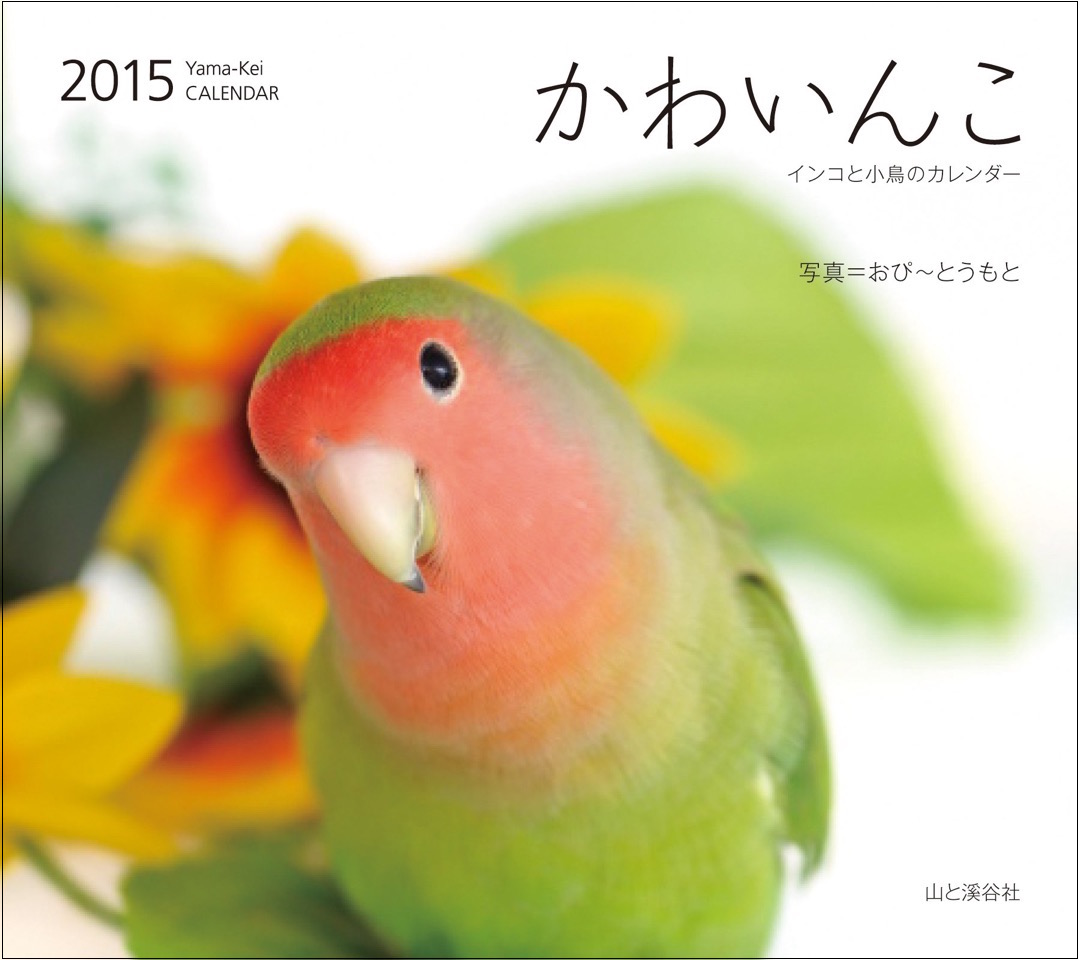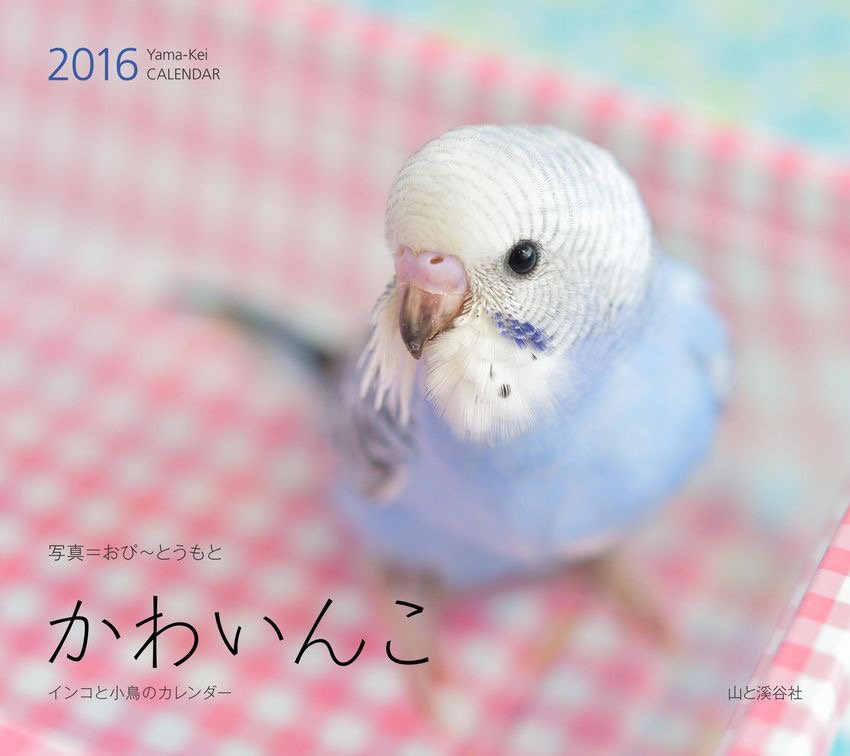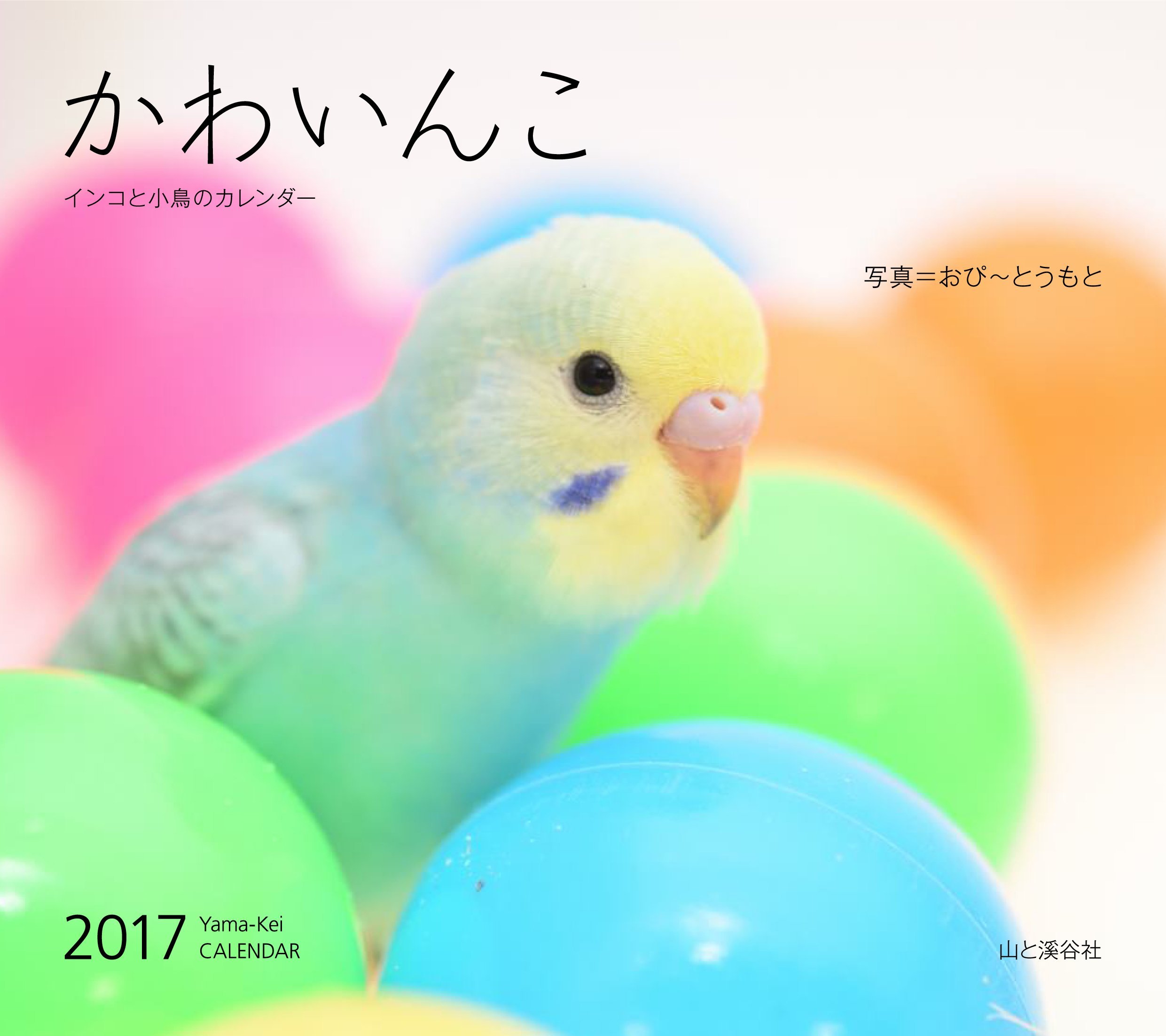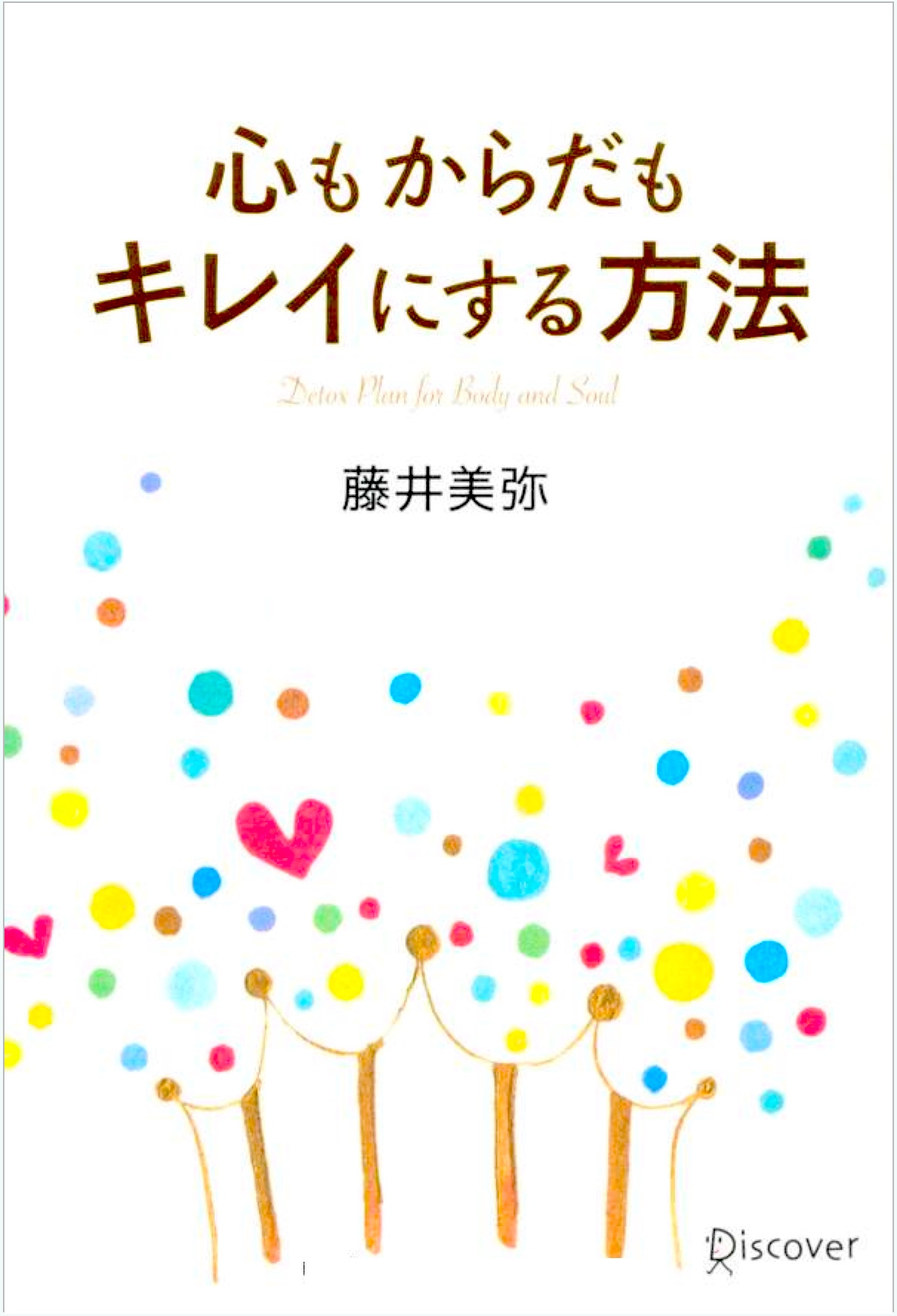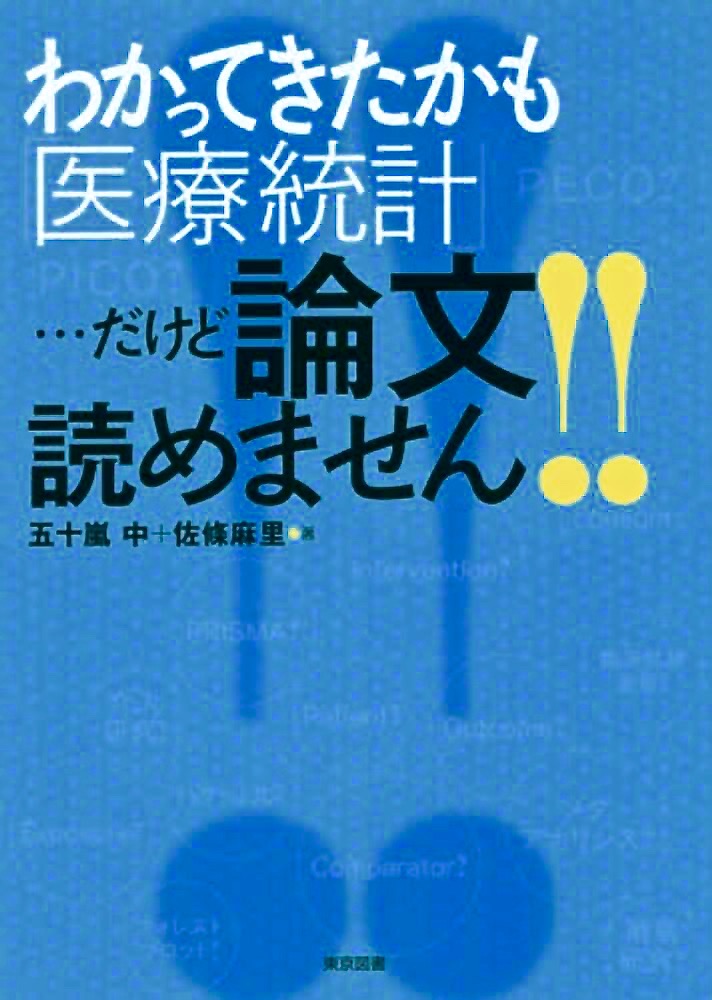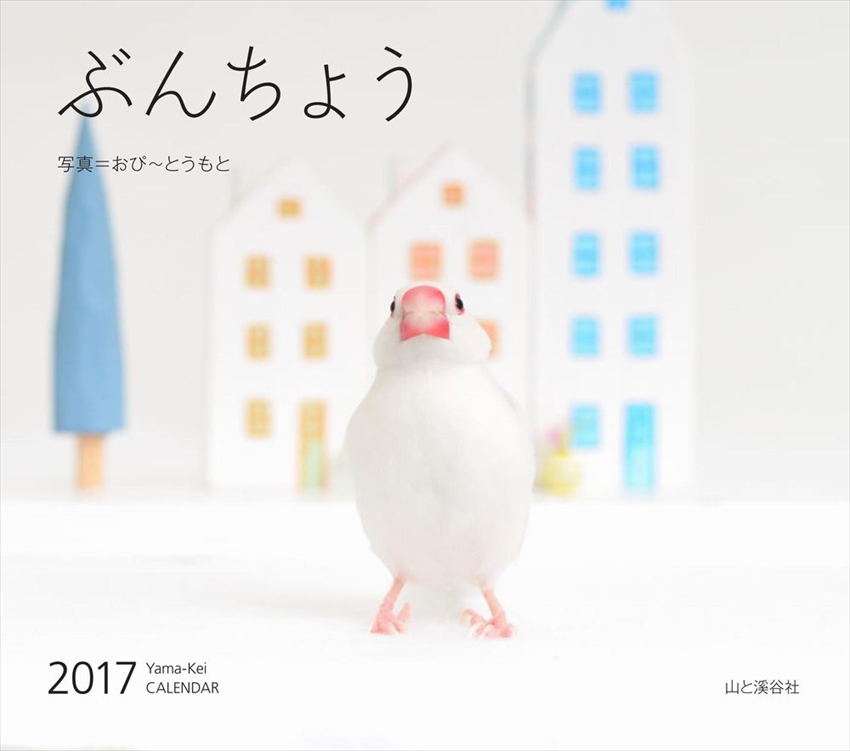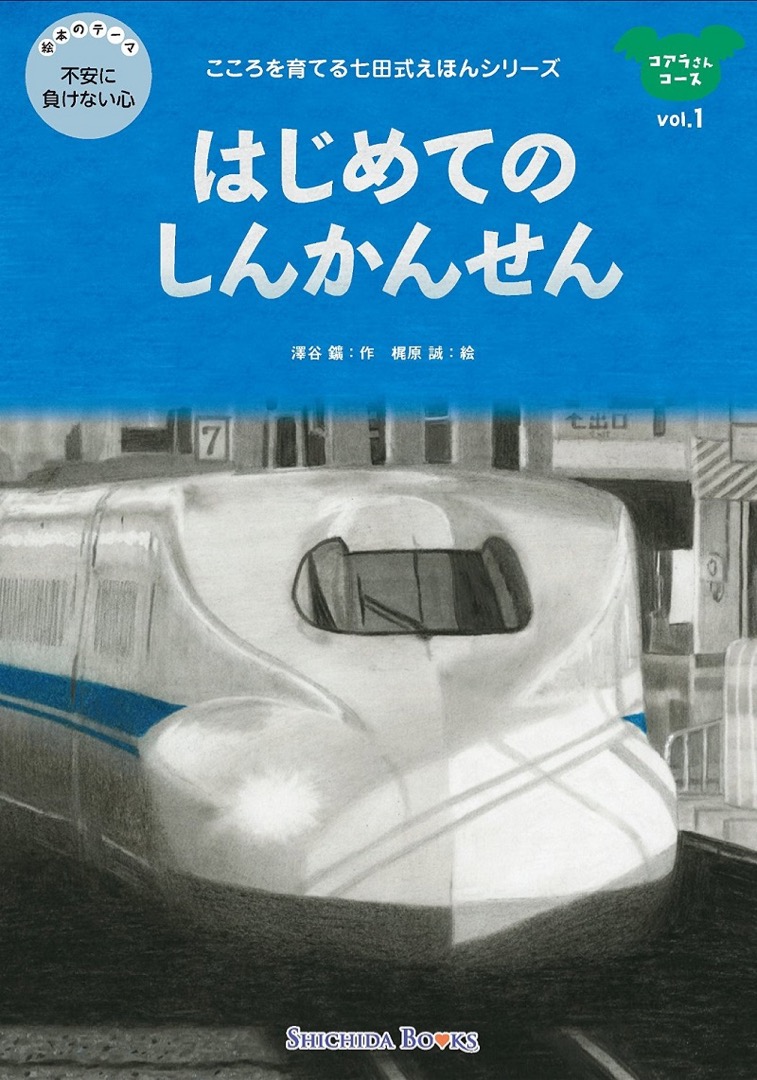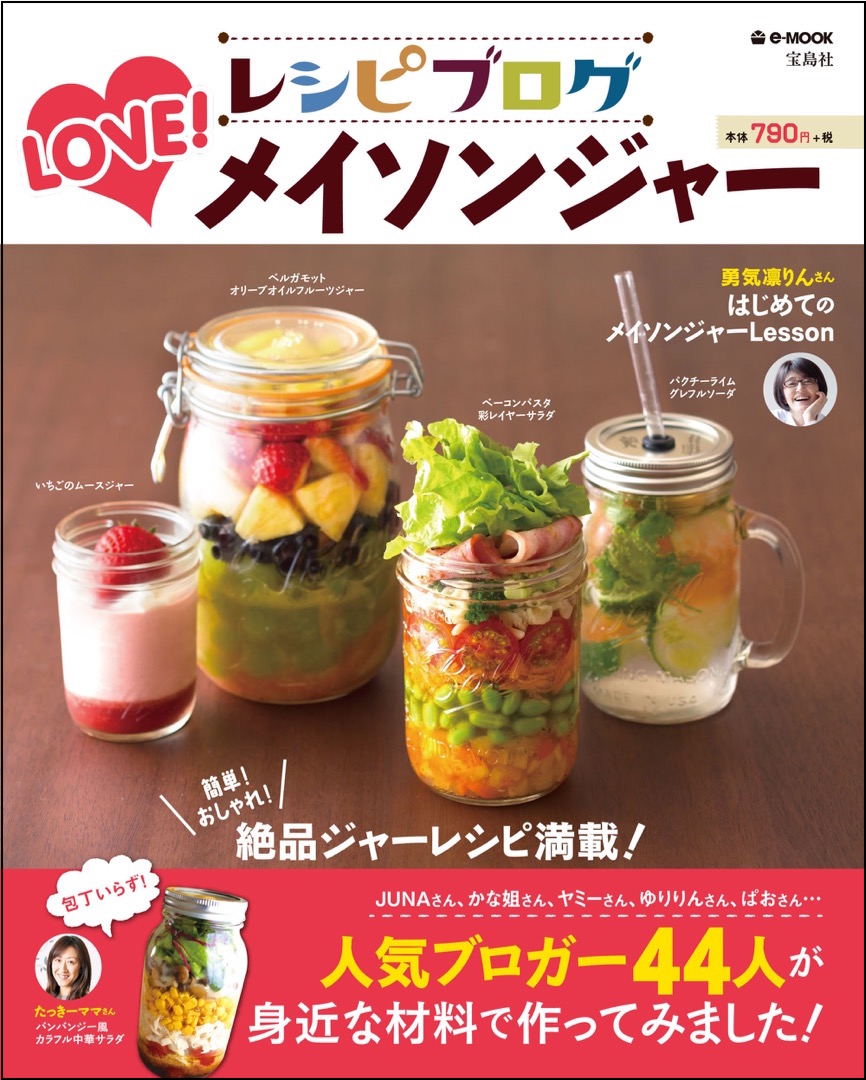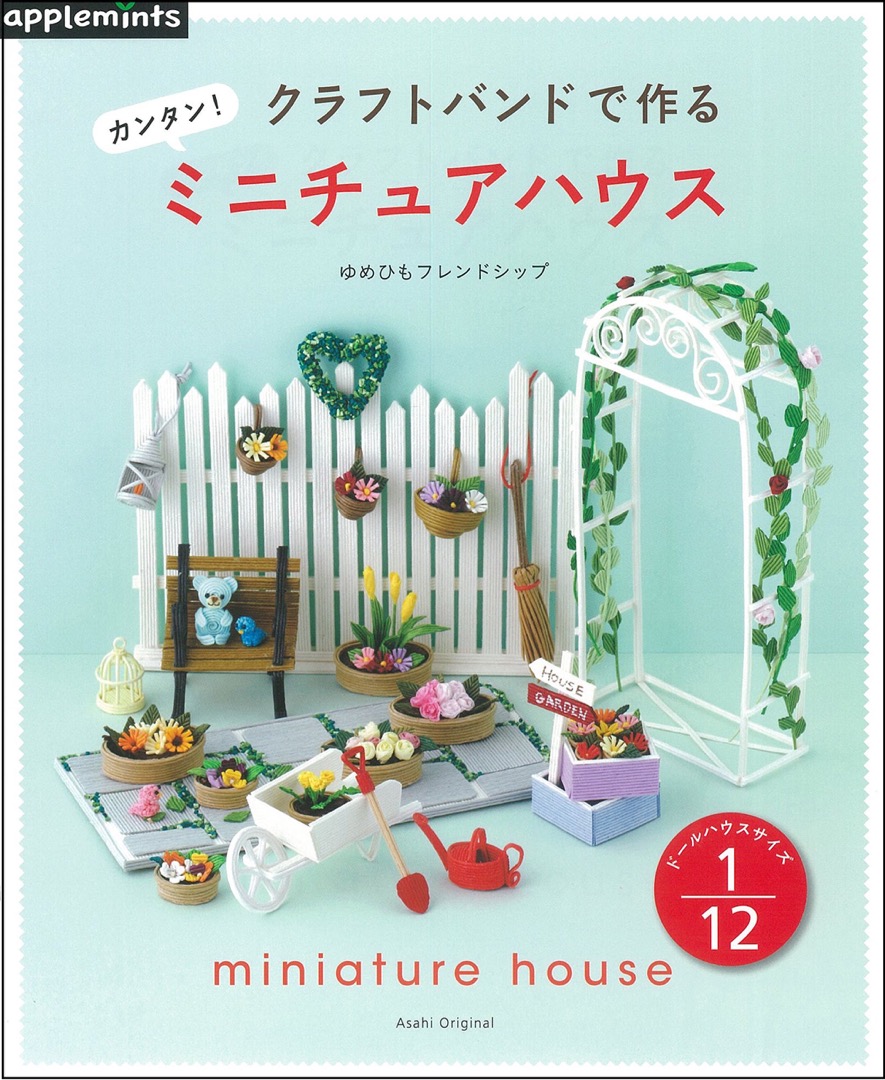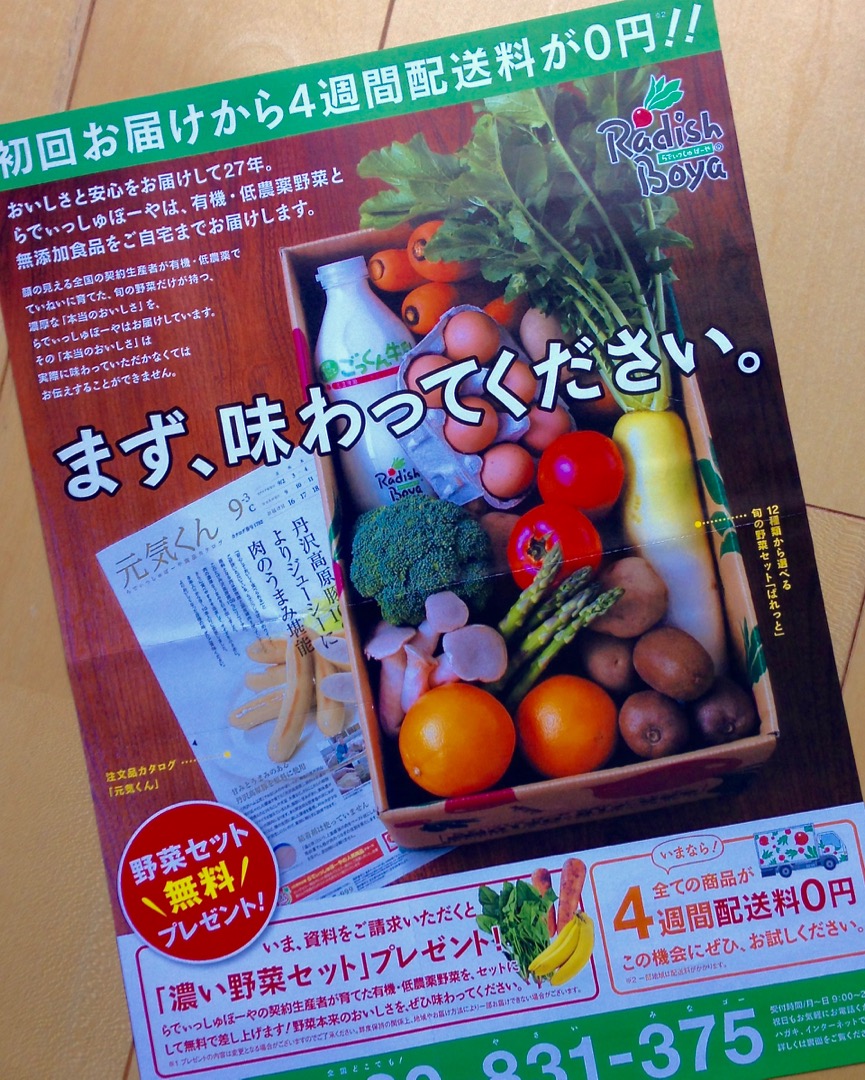
キャンペーン・ロゴ  さとうゆたか  2017年11月18日(土) 16:01
銭湯に貼ってありました。
さとうゆたか  2017年11月18日(土) 16:02 [修正]
こちらは昨年のもの。
本の表紙  さとうゆたか  2017年11月6日(月) 11:02
書名:幸せは白いTシャツ
著者:片岡義男
発行:株式会社ボイジャー
映画の題名  さとうゆたか  2017年10月1日(日) 8:48
きのう公開された映画。
細めの墨東をキレイに使ってくれている。
さとうゆたか  2017年10月1日(日) 8:59 [修正]
予告ムービーなどにも使われていた。
絵じてん  さとうゆたか  2017年8月29日(火) 15:34
書名:ことば絵じてん
著者:下薫
発行:東京書店
糖質オフのやせる作りおき  さとうゆたか  2017年8月9日(水) 9:22
書名:ぜんぶレンチン!
著者:牧田善二
発行:新星出版社
本の表紙  さとうゆたか  2017年8月1日(火) 15:45
書名:スタイルを持ち、身軽に暮らす
著者:石原左知子
発行:SBクリエイティブ
百合姫コミックスの作品にて  takumi  2017年7月23日(日) 21:39  HP
百合姫コミックス(一迅社)の漫画『ラブデス。〜短期集中連載集〜』の表紙に墨東くずれフォントが使われているのを見つけました。
タイトルと、作者名部分ですね。
さとうゆたか  2017年7月24日(月) 8:33 [修正]
このフォント、最近使用例を見ないな…と思っていたところです。
本の表紙  さとうゆたか  2017年7月12日(水) 16:05
書名:燃やすおかず つくりおき
著者:高橋善郎
発行:学研プラス
15年前のポケモン映画  takumi  2017年7月8日(土) 22:14  HP
2002年に公開されたポケットモンスターの映画『水の都の護神 ラティアスとラティオス』のロゴで墨東フォントが使われていました。
「ラティアスとラティオス」の部分ですね。
当時好きだった映画で、改めて何気なくチェックしたら、墨東フォントの存在に気付きました。
さとうゆたか  2017年7月9日(日) 8:37 [修正]
15年前の古いポスター…。
よくぞ、見つけてくれました〜〜。